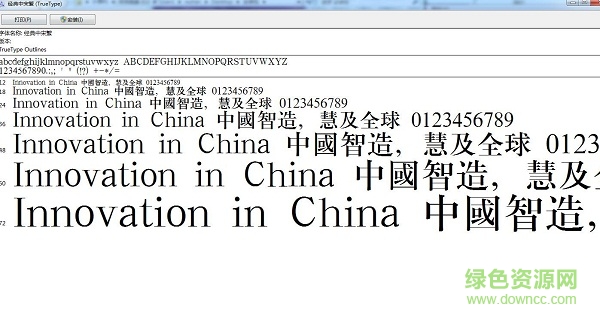
經(jīng)典中宋繁字體是一款適合正文排版使用的繁體字體,風(fēng)格樸實(shí),清晰爽目,筆畫線條粗細(xì)差別鮮明,小尺寸也能清晰顯示,可用于屏幕閱讀或是各類印刷產(chǎn)品中!
1.橫細(xì)豎粗,末端有裝飾部分;
2.整體字形挺拔俊秀,給人以悅目之感;
3.久讀不易疲勞、印刷適性好!